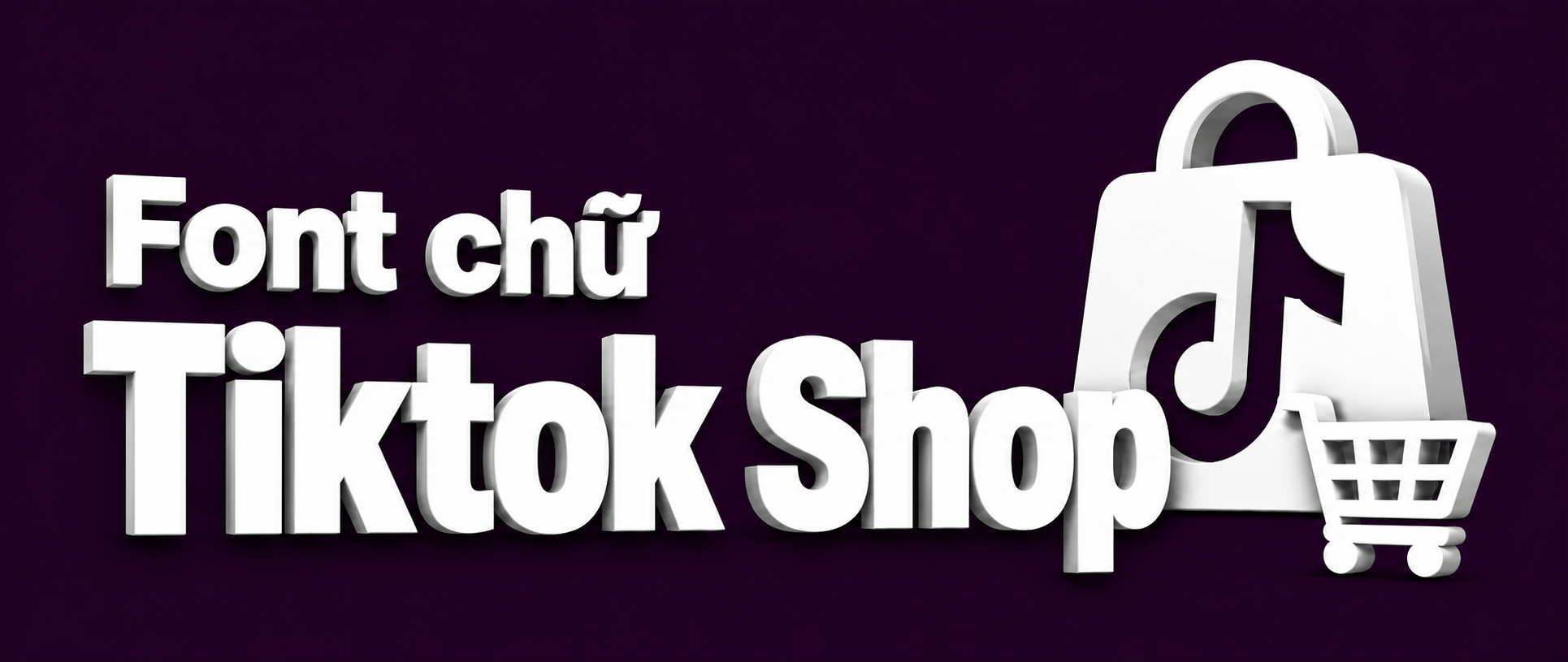
TikTok Shop là môi trường bán hàng rất nhanh. Người xem lướt qua sản phẩm trong vài giây, nhìn giá trong livestream, bấm vào voucher, so sánh deal và quyết định mua gần như ngay lập tức. Vì vậy, font chữ TikTok Shop không chỉ cần đẹp mà còn phải rõ, mạnh, dễ đọc trên màn hình điện thoại và hỗ trợ tiếng Việt tốt.
Một banner TikTok Shop đẹp thường không thắng vì có quá nhiều chữ. Nó thắng vì chữ đúng trọng tâm: tên sản phẩm rõ, ưu đãi nổi bật, giá đọc nhanh, CTA dễ bấm và phong cách hợp ngành hàng. Bài viết này gợi ý các font Việt hóa phù hợp để thiết kế ảnh sản phẩm, cover shop, voucher, flash sale, thumbnail video ngắn và khung livestream bán hàng.
Thiết kế TikTok Shop chủ yếu được xem trên điện thoại. Điều này làm font phải hoạt động tốt ở kích thước nhỏ, trên nền ảnh sản phẩm, trong video dọc, trong cover gian hàng và cả khung livestream có nhiều thông tin cùng lúc.
Nếu dùng font quá mảnh, chữ giá và voucher dễ chìm. Nếu dùng font quá cầu kỳ, dấu tiếng Việt có thể vỡ hoặc khó đọc. Nếu dùng quá nhiều kiểu chữ trong một thiết kế, người xem không biết nên nhìn vào đâu trước.
Với TikTok Shop, font nên phục vụ hành vi mua hàng. Tiêu đề cần bắt mắt. Giá cần đậm. Phần mô tả cần gọn. CTA như “Mua ngay”, “Áp mã”, “Freeship”, “Chốt đơn” cần nhìn rõ ngay cả khi ảnh bị thu nhỏ.
Một bộ thiết kế tốt thường dùng 2-3 font. Một font display cho headline hoặc deal lớn. Một font sans-serif rõ cho giá, mô tả và thông tin sản phẩm. Một font cá tính hơn có thể dùng cho sticker, nhãn “hot”, “new”, “sale sốc” hoặc thông điệp livestream.
TikTok Shop ưu tiên trải nghiệm mobile. Font cần có nét đủ dày, khoảng cách chữ rõ và không bị rối khi hiển thị trong ảnh vuông, ảnh dọc hoặc thumbnail video. Những phần quan trọng như giá, phần trăm giảm, mã voucher và tên sản phẩm nên dùng font rõ hơn font trang trí.
Các ngành hàng trên TikTok Shop thường có nhiều từ có dấu như mỹ phẩm, quần áo, đồ gia dụng, mẹ và bé, phụ kiện, hàng chính hãng, giảm giá, freeship. Font Việt hóa giúp dấu không lệch, không mất và không làm thiết kế thiếu chuyên nghiệp.
TikTok Shop cần sự chú ý, nhưng không nên khiến banner nhìn rẻ hoặc quá ồn. Font đậm, condensed, công nghệ hoặc sans-serif hiện đại sẽ phù hợp với deal, sản phẩm điện tử, phụ kiện, đồ gia dụng. Font thanh lịch hợp mỹ phẩm, thời trang, chăm sóc cá nhân. Font cute hợp mẹ và bé, đồ ăn vặt, đồ dùng học sinh.
Ảnh sản phẩm thường đã có nhiều chi tiết. Font cần đủ tương phản với nền, có thể đặt trong khung màu, badge, sticker hoặc vùng trống. Không nên đặt chữ mảnh trực tiếp lên ảnh nhiều texture như mỹ phẩm bóng, quần áo họa tiết hoặc đồ gia dụng nhiều chi tiết.
Một font tốt nên dùng được cho cover gian hàng, ảnh sản phẩm, poster flash sale, voucher, thumbnail video, livestream overlay và bài đăng social. Nếu một font chỉ đẹp ở headline lớn, hãy dùng nó làm điểm nhấn, không dùng cho toàn bộ hệ thống chữ.
Nhóm này hợp với phụ kiện điện thoại, thiết bị điện tử, đồ gia dụng thông minh, đồ thể thao, sản phẩm nam giới và các banner cần cảm giác nhanh, chắc, hiện đại.
Những font này hợp với chữ ngắn như “Flash Sale”, “Deal hôm nay”, “Freeship”, “Chỉ từ 99K”, “Bảo hành chính hãng”. Khi dùng cho ảnh sản phẩm, nên phối với màu tương phản cao như đen, trắng, đỏ, vàng, xanh cyan hoặc xanh đậm.
Đây là nhóm nên có trong mọi bộ thiết kế TikTok Shop. Font sans-serif giúp thông tin đọc nhanh, đặc biệt là giá, size, mã giảm, mô tả ngắn, công dụng và điều kiện khuyến mãi.
Font TH Namian Sans Serif - Tải về
Font TH Manisans - Tải về
Font TH Artega - Tải về
Font TH Tokyo - Tải về
Font TH Legacy Sans - Tải về
Font TH AQUXE - Tải về
Nhóm này rất hợp làm font nền cho hệ thống gian hàng. Bạn có thể dùng cùng một font sans-serif cho toàn bộ giá, mã voucher, mô tả ngắn và CTA để shop nhìn nhất quán hơn.
Livestream bán hàng cần chữ đập vào mắt nhanh. Các nhãn như “chốt đơn”, “giá live”, “deal sốc”, “mua 2 tặng 1”, “giảm 50%” nên dùng font mạnh hơn bình thường.
Font TH Astrophel - Tải về
Font TH Cungcap 12 - Tải về
Font TH Cungcap 6 - Tải về
Font TH Wilffer - Tải về
Font VL Monologue - Tải về
Font TH Morgaty - Tải về
Nhóm này nên dùng cho phần chữ lớn, không nên dùng cho mô tả dài. Với livestream, hãy giữ số lượng chữ ít: một dòng deal chính, một dòng giá, một CTA. Nếu màn hình live đã có người bán, sản phẩm, comment và icon, chữ càng phải gọn.
Không phải gian hàng TikTok Shop nào cũng cần font quá mạnh. Với mỹ phẩm, nước hoa, thời trang nữ, phụ kiện cao cấp hoặc chăm sóc cá nhân, font thanh lịch giúp ảnh sản phẩm tin cậy hơn.
Font chữ TikTok Shop nên giúp người xem đọc nhanh, hiểu nhanh và ra quyết định nhanh. Hãy chọn font Việt hóa rõ dấu, dùng font mạnh cho deal, font sans-serif cho giá và font thanh lịch hoặc cute theo đúng ngành hàng.